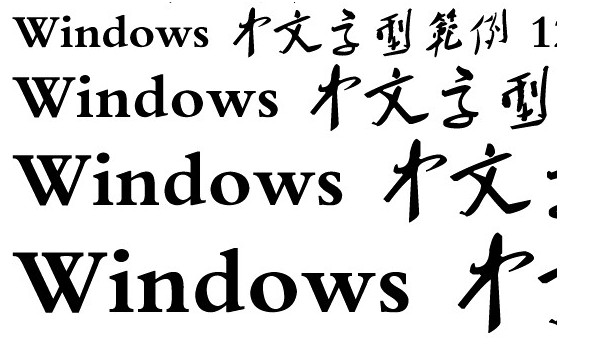
毛澤東草書(shū)字體是一款偉大領(lǐng)袖毛主席的字體,毛主席草書(shū)風(fēng)格雄渾,力道蒼勁,在很多設(shè)計(jì)眼里都是電腦必備字體,趕緊下載吧。
毛澤東是老一輩無(wú)產(chǎn)階級(jí)革命家,當(dāng)代杰出詩(shī)人。他的詩(shī)詞是革命現(xiàn)實(shí)主義與革命浪漫主義相結(jié)合的典范,繼承和發(fā)展了古詩(shī)詞的傳統(tǒng),創(chuàng)造了革命的政治內(nèi)容和完美的藝術(shù)形式高度統(tǒng)一的詩(shī)篇。它思想內(nèi)容強(qiáng),藝術(shù)境界高,在人民大眾中廣為傳頌,給人以強(qiáng)大的鼓舞力量。中國(guó)草書(shū)經(jīng)廣大書(shū)家的創(chuàng)造,集眾美于一體,有豐富的美學(xué)內(nèi)涵,達(dá)到很高的藝術(shù)境界。它有氣勢(shì)、有力度、有神韻,生動(dòng)活潑,柔韌雄強(qiáng),彰顯了中華民族精神。